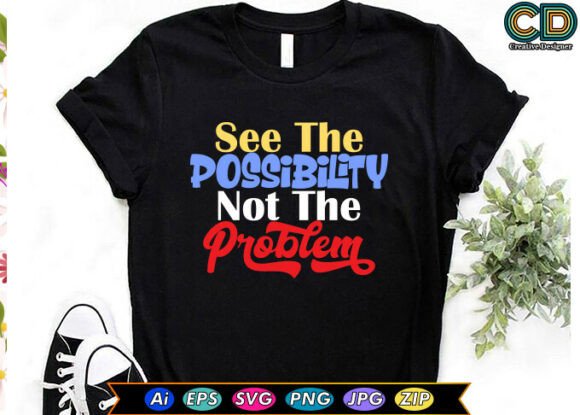
SEE the POSSIBILITY NOT the PROBLEM
์˜ฌ๋ฐ”๋ฅธ ๋””์ž์ธ ์š”์†Œ๋ฅผ ์ฐพ๋Š” ๊ฒƒ์€ ์–ด๋ ค์šธ ์ˆ˜ ์žˆ์ง€๋งŒ SEE the POSSIBILITY NOT the PROBLEM๋Š” ์ž‘์—…์„ ์ฆ‰์‹œ ํ–ฅ์ƒ์‹œํ‚ค๋Š” ๋›ฐ์–ด๋‚œ ์ปฌ๋ ‰์…˜์„ ์ œ๊ณตํ•ฉ๋‹ˆ๋‹ค.